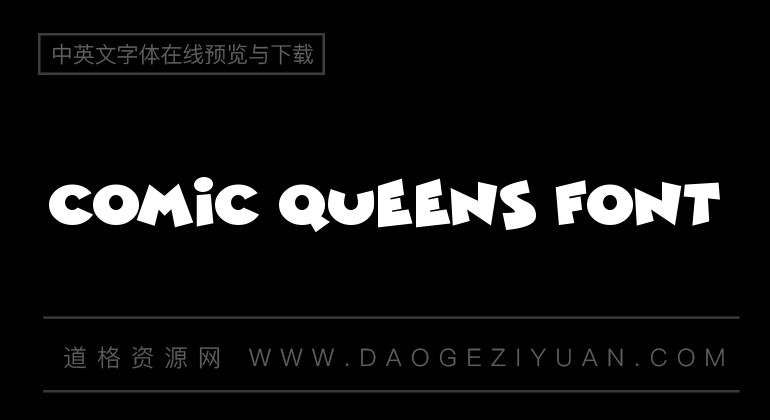
Comic Queens Font
Comic Queens Font 是一种英文字体,其风格非常适合漫画和卡通等相关设计使用。该字体的特点是大写字母的线条弯曲,形状像是手写的。每个字符都非常活泼,有很强的可读性和辨识度。此外,Comic Queens Font 还包含了一些特殊符号和标点符号,可以满足各种不同的设计需求。 由于 Comic Queens Font 的设计极具趣味性和独特性,因此在许多儿童书籍、漫画、卡通片等方面都得到了广泛的应用。使用 Comic Queens Font 的设计作品,往往能够传达出轻松、有趣的氛围,引起读者的共鸣。
Comic Queens Font是一款非常不错的手写艺术字体,具有很好的视觉感,适合于文化类的宣传设计、商业类品牌的广告和产品包装设计以及个性化文字排版等较多场景。